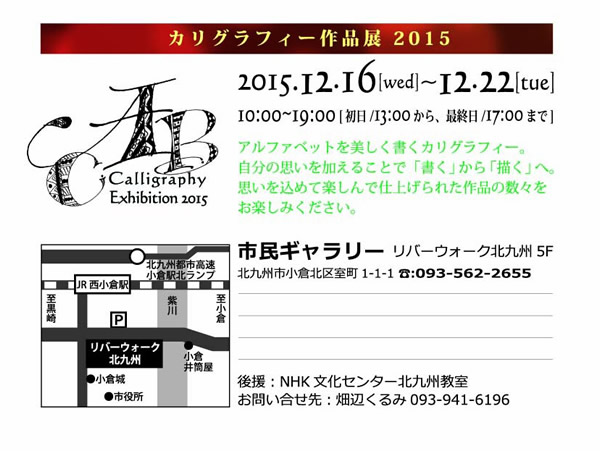
カリグラフィー作品展
Calligraphy文字もじ展 21st
【出展者】石下裕子、進藤和美、松井康子、山崎みどり
本当に「蔵」のギャラリーです。
居心地もいいですし見ごたえのある作品展です!
DMはウラも楽しい。石下裕子さんのテガキです!
第3回 PONTE NOTTE 生徒作品展
大阪梅田の便利なところにあるギャラリーです。
第7回 丸善 世界の万年筆展 手書の愉しさを味わう
The Art of Lettering 日本カリグラフィースクール
レギュラーコース講師 カリグラフィー作品展
◇カリグラフィーのミニレッスンとデモンストレーション
3/2(水)澤田 未恵、3/7(月)阿部 久代、3/8(火)ふくだいくこ
◇万年筆で描くオリジナルシグネチャー
3/3(木)相田英子、渋谷登志子
LETTERSNOW カリグラフィー作品展 Vol.1
会場の様子をお届けいたします。
1F、2Fに通じる階段には作品の展示、2Fは販売。
土曜日、日曜日にはデモンストレーションも行いました。
連日たくさんの方においでいただき、賑やかな作品展になりました。
カリグラフィー Pointed Pen Variations 第2回大阪教室展
カリグラファーズ・ギルド会員の中村仁美さんのPointed Pen大阪教室の作品展です。
日頃の成果をご覧くださいませ~。
福岡のカリグラファー初島さつきさんから作品展のご案内が届きました。
文字の旅二千年 手書きアルファベットからデジタルフォントまで
第6回スタヂオポンテ作品展
今回の作品展は、手書き文字の歴史を印刷媒体の歴史と重ね合わせながら展示し、手書き文字(アルファベット)が印刷媒体へどのように影響を与え、逆に印刷媒体も手書き文字に影響を与えていることなどを紹介したいと 思ってい ます。
具体的には、約2千年前に生まれたRoman Capitalに始まり、Rustic, Uncial,Insular- half uncial. Carolingian, Protogothic, Gothic textura, Gothic quadrata,Rotunda, Batarde, Humanist, Italic, Fracture, Flemish, Copperplate, Foundationalの代表的な書体の作品を第1展示室(博物館)に活版印刷と写植機と共に展示して、文字の歴史を見せる予定です。
活版印刷の展示は、日本で初めて作られた本木昌造作の活字の展示と、福岡で長く活版に携わってこられた文林堂さんの時代を感じさせる展示、最近新 たに見直されてきた活版の世界を若手デザイナーの視点で見せてくれるOLD PRESSさんの展示があります。
写植は、日本で写植が最盛期だった1960年代からずっとこの世界に関わってこられた伊藤さんが、写植のノウハウを実際見せてくださいます。
10年後の写植生誕100年までは、なんとか写植を消滅させたくないという情熱とともに、いろいろな分野の方とのコラボレーションを試みられてい る作品の展示(木版画、詩人とのコラボ作品が展示予定)が見ものです。
デジタルフォントは、人気書体の開発で全国的に有名な(株)フォントワークスさんの最新書体のパネル展示と、デジタルフォントの作られる様子を動 画で常時流す予定です。フォントデザイナーの藤田さんは前身が写研(写植の会社)で、モノタイプの小林章さん、文字道の伊藤さんともお友達です。
歴史的な書体の他に、21世紀的なカリグラフィー作品も第2会場に展示します。
遠くからでも来た甲斐があった!と、必ず思ってもらえる展示にいたします!!
銀座の小さな写字室
小さなイニシャルの装飾文字を展示します。